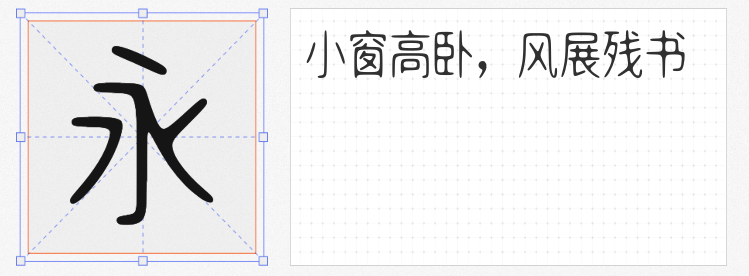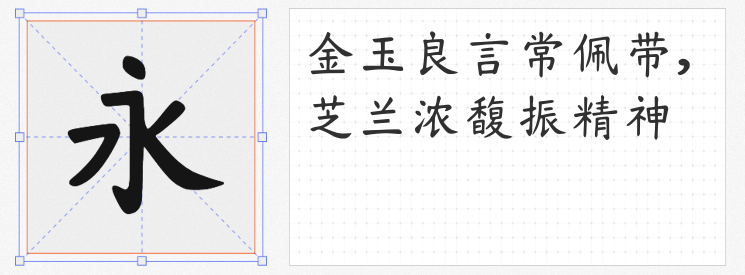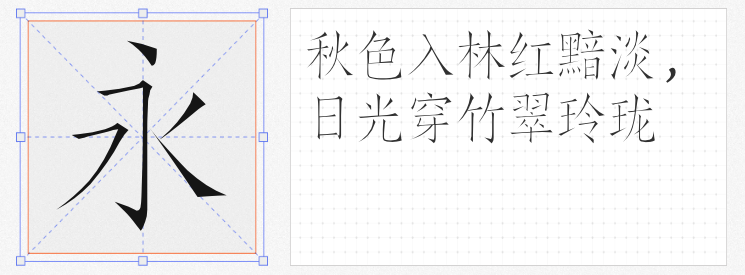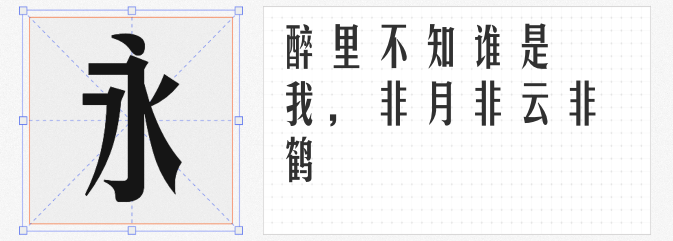
在极简主义设计浪潮中,字体的选择往往决定着视觉表达的纯粹度与高级感。以下四款免费商用字体,以简洁的线条、克制的结构与独特的文化基因,成为极简设计的理想搭档。它们不仅满足商业用途的合规性,更以轻盈的姿态为作品注入呼吸感。
作为AI技术赋能的产物,天空仿宋体将传统仿宋的“横细竖粗、撇捺舒展”特征与现代算法深度融合。去除了传统仿宋的繁复装饰,仅保留骨架的简洁与笔画的韵律,形成一种克制而优雅的极简气质。其字形修长挺拔,中宫紧凑却不拥挤,适用于文化类海报、艺术展览视觉、书籍排版等场景,以科技感诠释东方美学的留白哲学。
以珠海先贤苏曼殊墨宝为灵感,鼎猎珠海体将书法中的飞白与顿挫转化为极简的几何线条。笔画粗细统一,转折处以圆角替代锐利棱角,既保留书法韵味,又呈现现代设计的秩序感。其字形结构疏朗开阔,字间距自然,适合城市宣传、文旅品牌、公益海报等场景,以极简笔触传递地域文化的温度与诗意。
“似水凝聚,浑圆无锋”是明达明达无锋体的核心设计理念。这款字体彻底摒弃传统汉字的笔锋与折角,以等宽笔画与圆润弧度构建字形,中宫放松、布局舒展,营造出一种“无争”的视觉呼吸感。其细长的字身与克制的线条,适用于科技品牌、极简主义包装、数据可视化等场景,以“无锋”的姿态传递理性与包容。
华光俊秀体以“高挑修长”为视觉符号,在极简框架中融入动态平衡。笔画粗细对比强烈,横画纤细而竖画挺拔,刚劲中透出柔美;字身比例拉长,却通过微妙的弧度避免僵硬感。其应用场景广泛,从品牌LOGO到电商海报,从影视片头到动漫字体,均能以极简形态传递现代感与生命力。
四款字体或以AI重构传统,或以人文沉淀极简,或以无锋诠释克制,或以刚柔演绎张力,共同诠释了极简设计的核心——少即是多,简即是深。无论是追求科技感、文化性,还是理性与柔美的平衡,这些免费商用字体都能成为设计师手中的“留白之笔”,让作品在简洁中迸发无限可能。